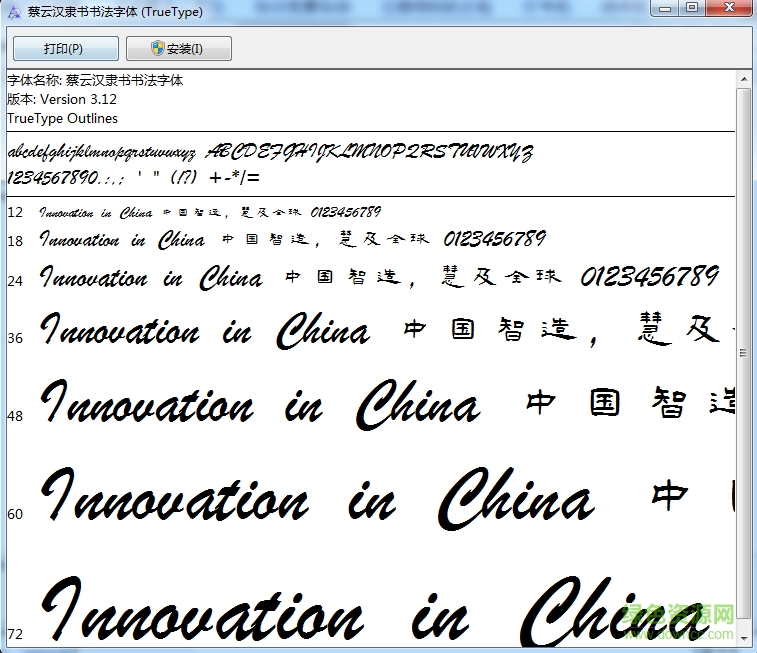
蔡云漢隸書(shū)書(shū)法字體是一款精美簡(jiǎn)潔的書(shū)法字體,以隸書(shū)書(shū)法為骨創(chuàng)作而成,充滿了飄逸娟秀之感,喜歡的朋友就來(lái)綠色資源網(wǎng)下載吧!
蔡云漢,本名蔡昌,號(hào)明云居士。山東菏澤人,好三教性命之學(xué)。從事書(shū)法和傳統(tǒng)文化教育工作,蒙庭訓(xùn),好翰墨。幼時(shí) 學(xué)柳,少致力于顏,長(zhǎng)則涉歷代諸法帖,后以金文氣韻入草書(shū)之中。于傳統(tǒng)書(shū)法的學(xué)習(xí)和繼承中,倡導(dǎo)書(shū)法文化的實(shí)際功 用-------文以載道,即從書(shū)法學(xué)習(xí)和創(chuàng)作審美的過(guò)程中,使自己和他人體會(huì)到中華文化的淑世價(jià)值,于是修身養(yǎng)心,歸于 中正平和。
蔡云漢隸書(shū)書(shū)法字體是一款造型獨(dú)特有個(gè)性的書(shū)法藝術(shù)字體,看起來(lái)既瀟灑又工整,適用于廣告設(shè)計(jì)、平面設(shè)計(jì)、產(chǎn)品包裝、報(bào)刊雜志等領(lǐng)域。